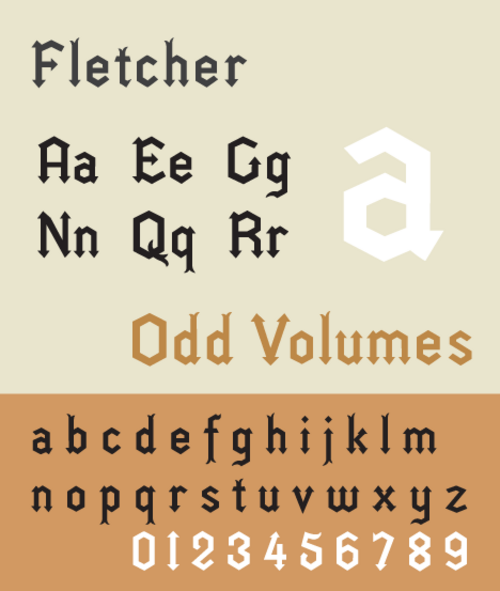
| カテゴリ | セリフ |
| 分類 | ブラックレター |
| デザイナー | テオフィル・ボードワール ダン・X・ソロ(復活) |
| 鋳造所 | ボードゥワール・アンド・シー ソロタイプ |
| リリース日 | 1865年頃 |
フレッチャーは、パリのテオフィル・ボードワール (1833-1903) の鋳造所でデザインされた 19 世紀のブラックレター書体の復活に付けられた名前です。この書体は、1870 年代の多くの本のタイトル ページに登場します。ダン・X・ソロの復活は、ボードワール & Cie. の見本に基づいており、読みやすさを向上させるためにいくつかの文字が変更されています。
書体は幾何学的に構成されており、ペンの影響が見られますが、曲線のストロークはなく、ある意味ではジョナサン・バーンブルックの 1990 年のBastard書体を予期しています。